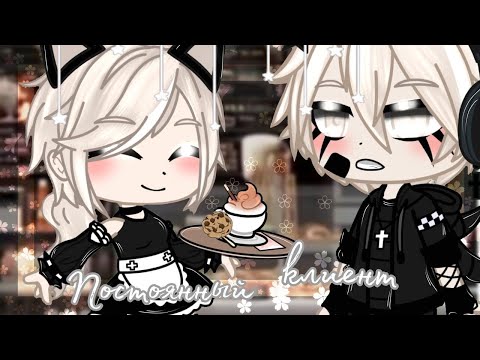
Как использовать прикольные шрифты на русском: советы по созданию уникальных текстов и привлекательной визуализации
Шрифты играют важную роль в дизайне и визуальной коммуникации. В этой статье мы предлагаем вам несколько идей и советов, как использовать прикольные шрифты на русском языке для создания оригинальных и запоминающихся текстов в различных проектах.
Используйте непривычные шрифты для презентаций: например, космическую тематику можно подчеркнуть шрифтом, имитирующим печать отпечатков пальцев, а для исторических проектов можно использовать архаические исчезнувшие шрифты.
Создайте логотип в уникальном шрифте: выберите шрифт, который будет идентифицировать ваш бренд. Это может быть расшитый, сказочный шрифт для детской компании или грубый, съедобный шрифт для фаст-фуда.
Смешивайте разные стили и шрифты: создайте контрастные сочетания прямых и курсивных шрифтов, жирных и тонких, чтобы создать уникальный и эффектный визуальный образ.